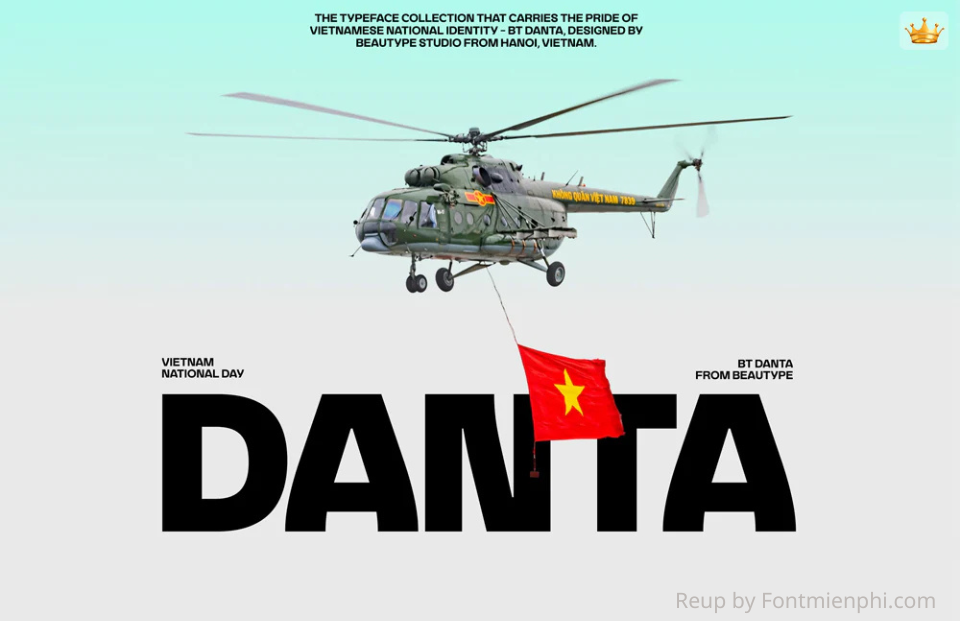
BT Danta – Nét chữ của người Việt, tâm hồn của người Việt
Điểm tự hào lớn nhất và cũng là linh hồn của Font Chữ Việt chính là BT Danta (Bộ font Dân ta). Đây không chỉ là một bộ phông chữ thông thường, mà là một dự án mang đậm tinh thần dân tộc. “Dân ta” được thiết kế dựa trên sự thấu hiểu sâu sắc về thói quen, ngôn ngữ và văn hóa của người Việt, mang đến những nét chữ vừa giữ được sự mộc mạc, gần gũi, vừa đáp ứng trọn vẹn các tiêu chuẩn thẩm mỹ hiện đại. Bộ font này được tinh chỉnh kỹ lưỡng để hiển thị sắc nét trên mọi giao diện, từ website, ứng dụng đến các ấn phẩm in ấn.